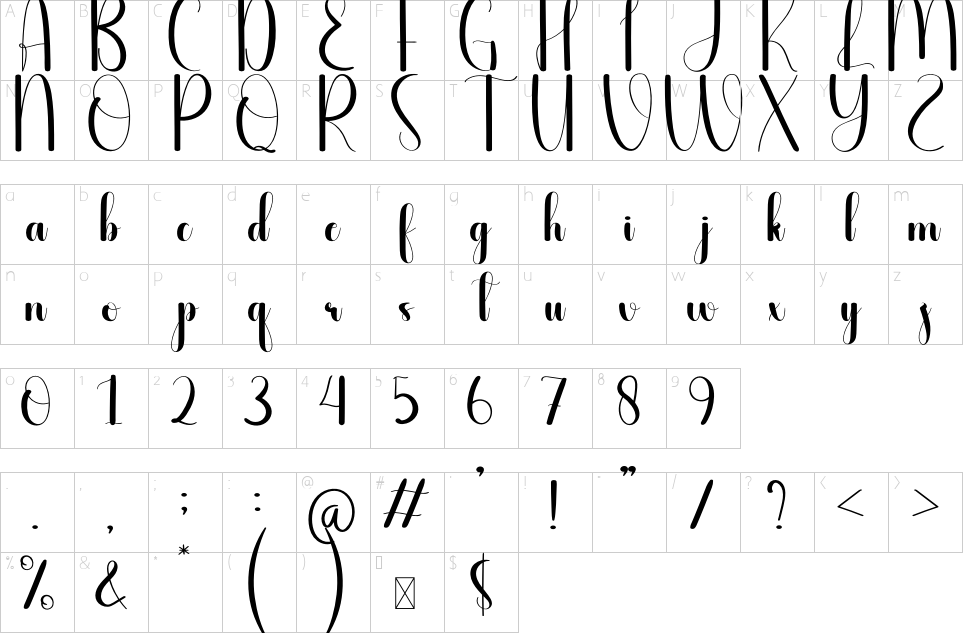
Aqui está uma descrição em português do Brasil para a página de download da fonte ‘Amellia Font’, respeitando os requisitos: A fonte ‘Amellia’ oferece uma experiência gráfica fluida e elegante, ideal para criar materiais diversos. Desenhada pelo designer William Jhordy, esta fonte garante um estilo único e sofisticado. Com sua versatilidade e precisão, ‘Amellia’ é a escolha perfeita para projetos que exigem um toque de sofisticação e criatividade. A fonte ‘Amellia’ está disponível tanto para sistemas Windows quanto para Mac, permitindo que você use sua beleza em qualquer plataforma. Com 364 downloads desde sua disponibilização, já é claro que muitos usuários apreciam a qualidade e a versatilidade desta fonte. ‘Amellia’ é uma escolha ótima para designers, gráficos ou qualquer pessoa que busque uma fonte de alta qualidade e estilo moderno. Descubra por si mesmo o que a ‘Amellia’ pode fazer para tornar seus projetos ainda mais únicos.